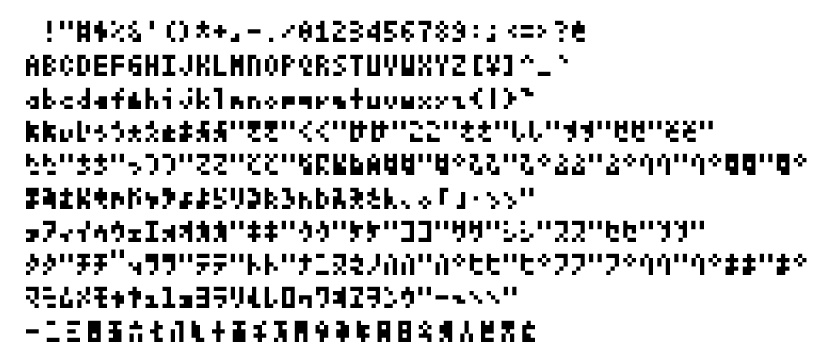
5x3pixel font(5×3ピクセル文字)
5×3のピクセルで製作したフォントです。 なお、このフォントは"FontStruct"というサイトで製作しました。 https://fontstruct.com/ This font was created using 5x3 pixels. This font was created using a website called "FontStruct". 商用利用可能(自己責任)、反社会的利用禁止でお願いします。 また、フォントの特性上視認性は期待できませんのであしからず。 Commercial use is permitted (at your own risk), but please refrain from anti-social use. Also, please note that due to the characteristics of the font, visibility cannot be expected. 収録文字 Recorded characters: !"#$%&'()*+,-./0123456789:;<=>?@ ABCDEFGHIJKLMNOPQRSTUVWXYZ[¥]^_` abcdefghijklmnopqrstuvwxyz{|}~ ぁあぃいぅうぇえぉおかがきぎくぐけげこごさざしじすずせぜそぞ ただちぢっつづてでとどなにぬねのはばぱひびぴふぶぷへべぺほぼぽ まみむめもゃやゅゆょよらりるれろゎわゐゑをん、。「」・ゝゞ ァアィイゥウェエォオカガキギクグケゲコゴサザシジスズセゼソゾ タダチヂッツヅテデトドナニヌネノハバパヒビピフブプヘベペホボポ マミムメモャヤュユョヨラリルレロヮワヰヱヲンヴヵヶー~ヽヾ 一二三四五六七八九十百千万円令和年月日今明人世界広